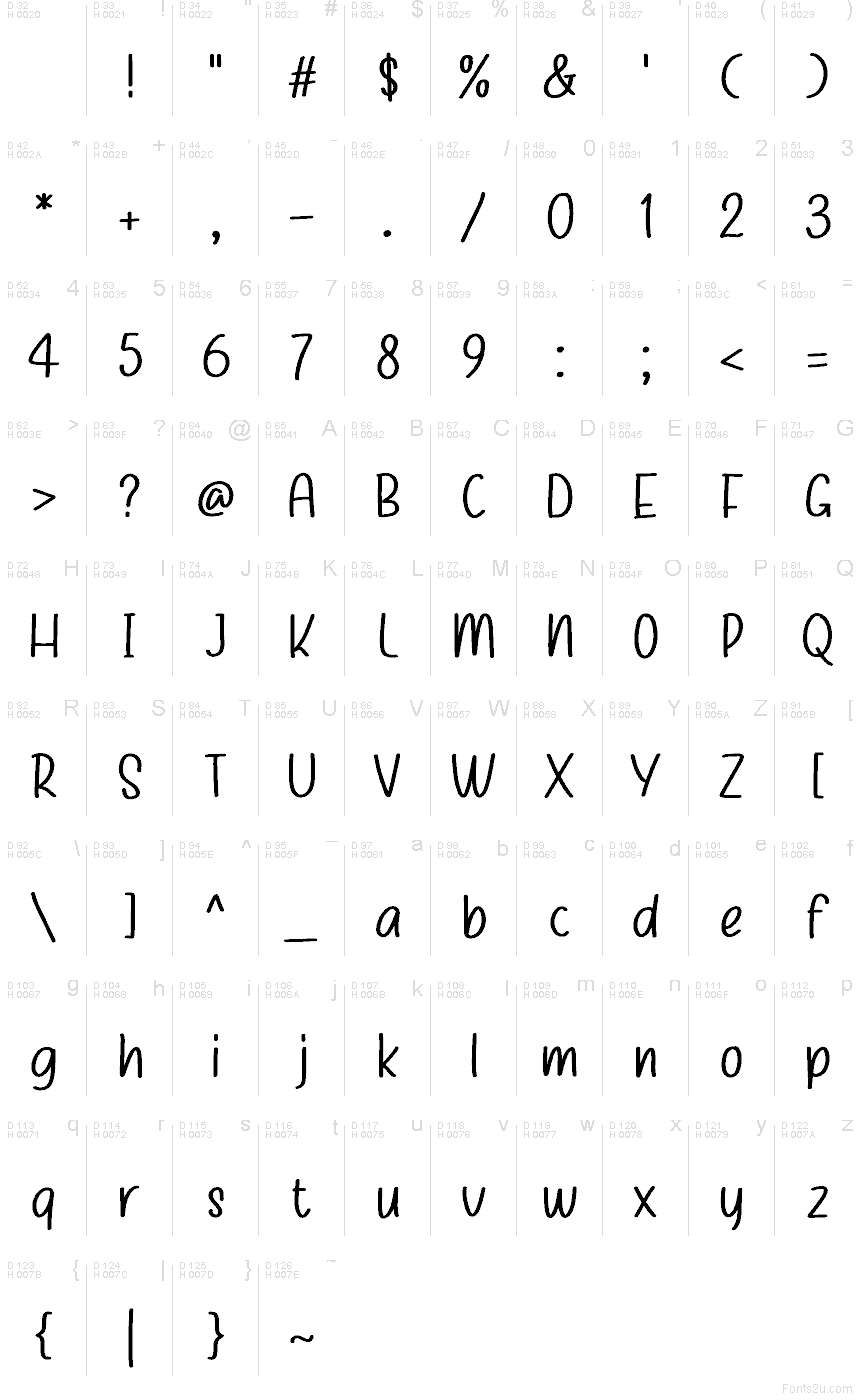
Spirit Sarov
La police Spirit Sarov, créée par Hello Good Studio, est une écriture manuscrite gratuite aux lettres hautes et étroites, dotée de tracés doux et arrondis. Son style est décontracté et légèrement informel, avec un rythme linéaire qui garde l'ensemble aéré et lisible plutôt que chargé.
Spirit Sarov est une police gratuite idéale pour vos logos, votre image de marque, des titres de blog, des faire-part de mariage, des citations graphiques ou vos packagings. Son tracé manuscrit et fluide apporte une touche personnelle sans jamais paraître brouillon, surtout lorsqu'elle est associée à des mises en page épurées et à des textes courts.